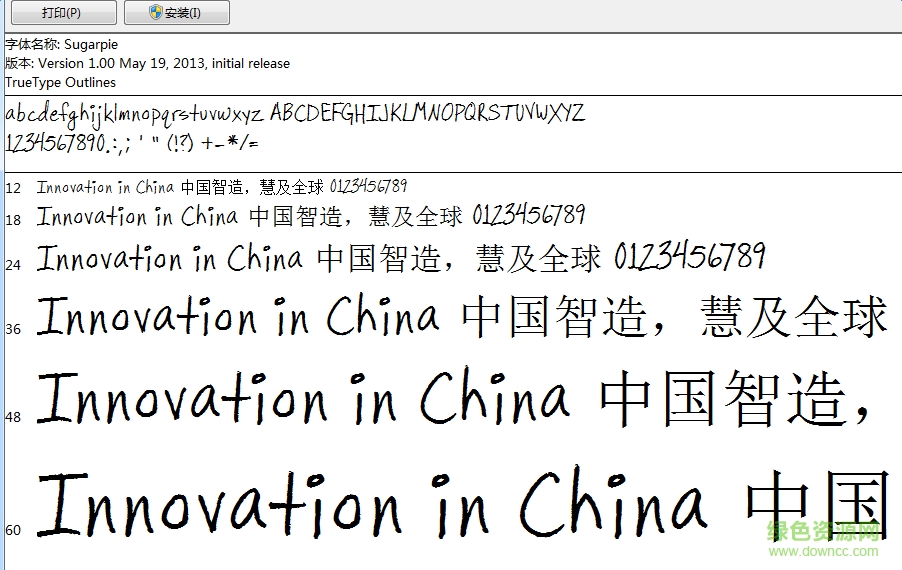
sugarpie
sugarpie字體是一款超好用的個(gè)性英語字體,該字體可以適用于名片設(shè)計(jì)、平面設(shè)計(jì)、廣告設(shè)計(jì)、報(bào)紙雜志、企業(yè)LOGO、商標(biāo)注冊(cè)、電視臺(tái)廣告等領(lǐng)域,有喜歡的網(wǎng)友可免費(fèi)下載收藏。